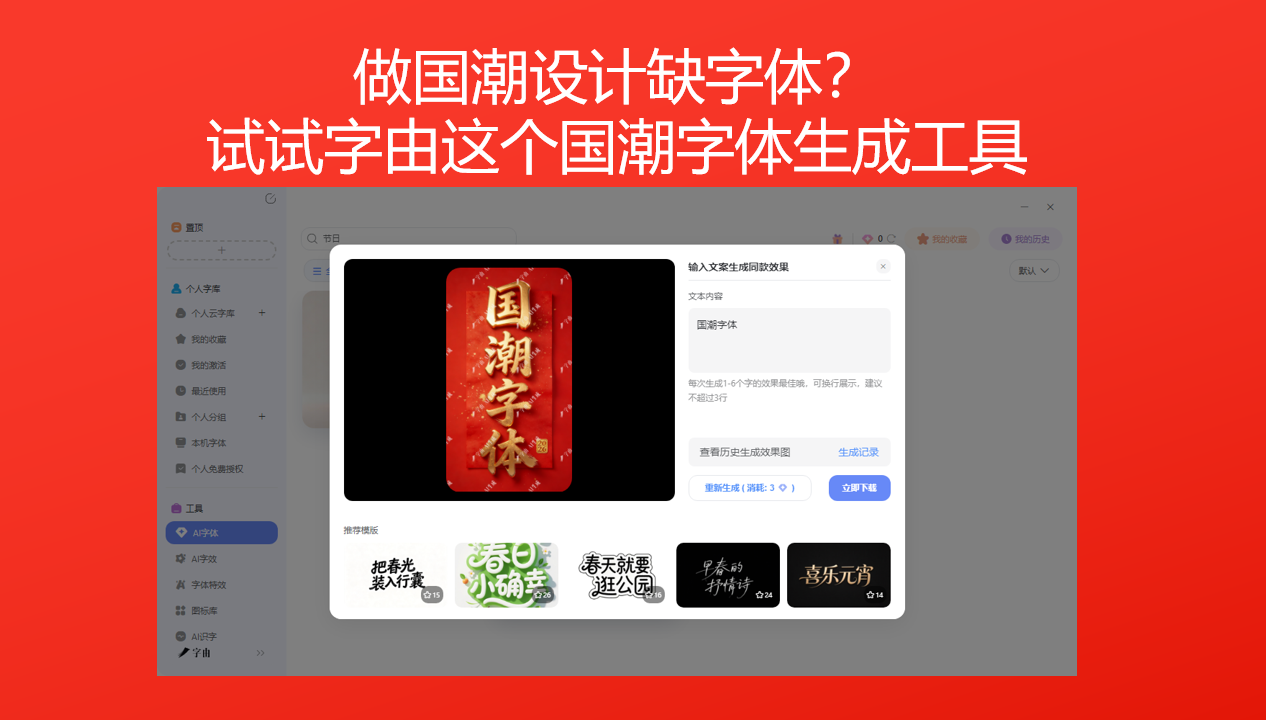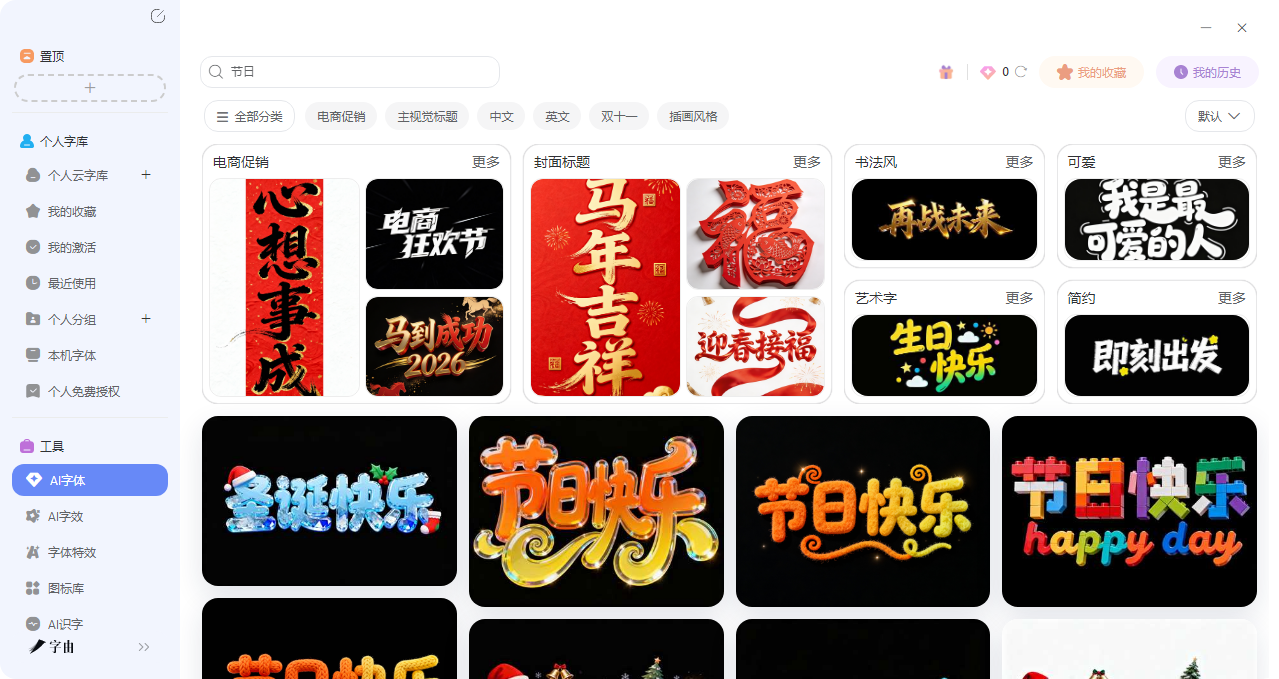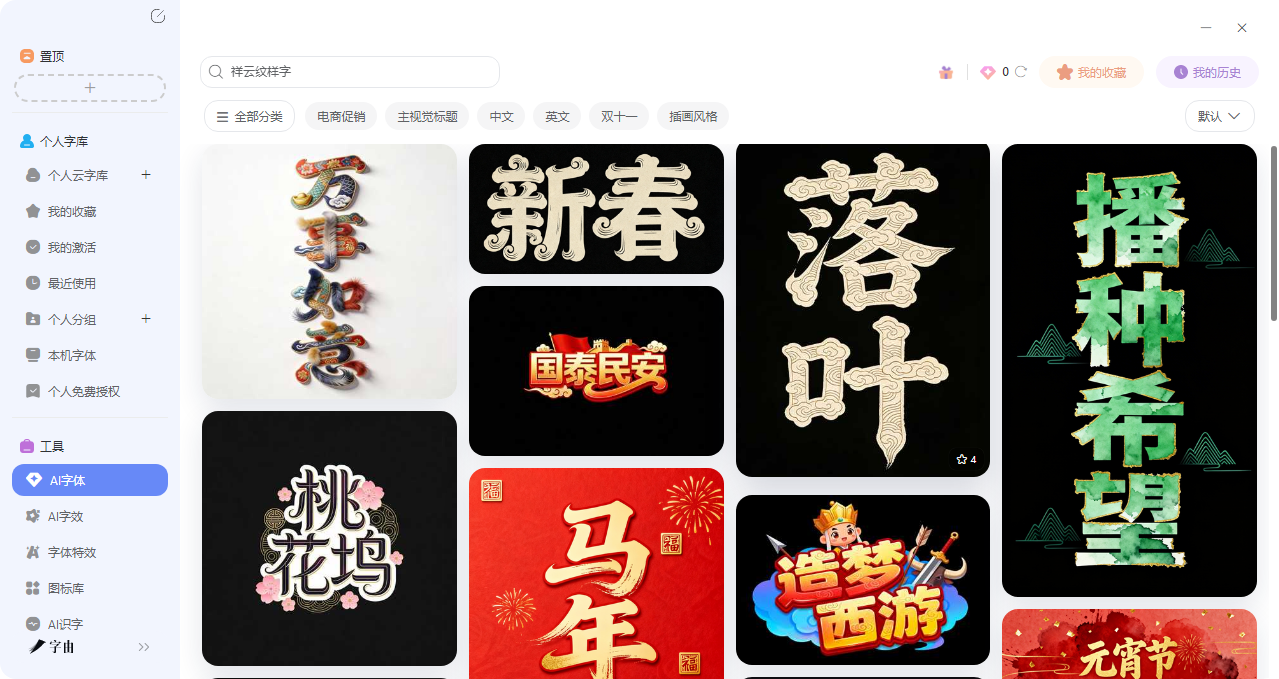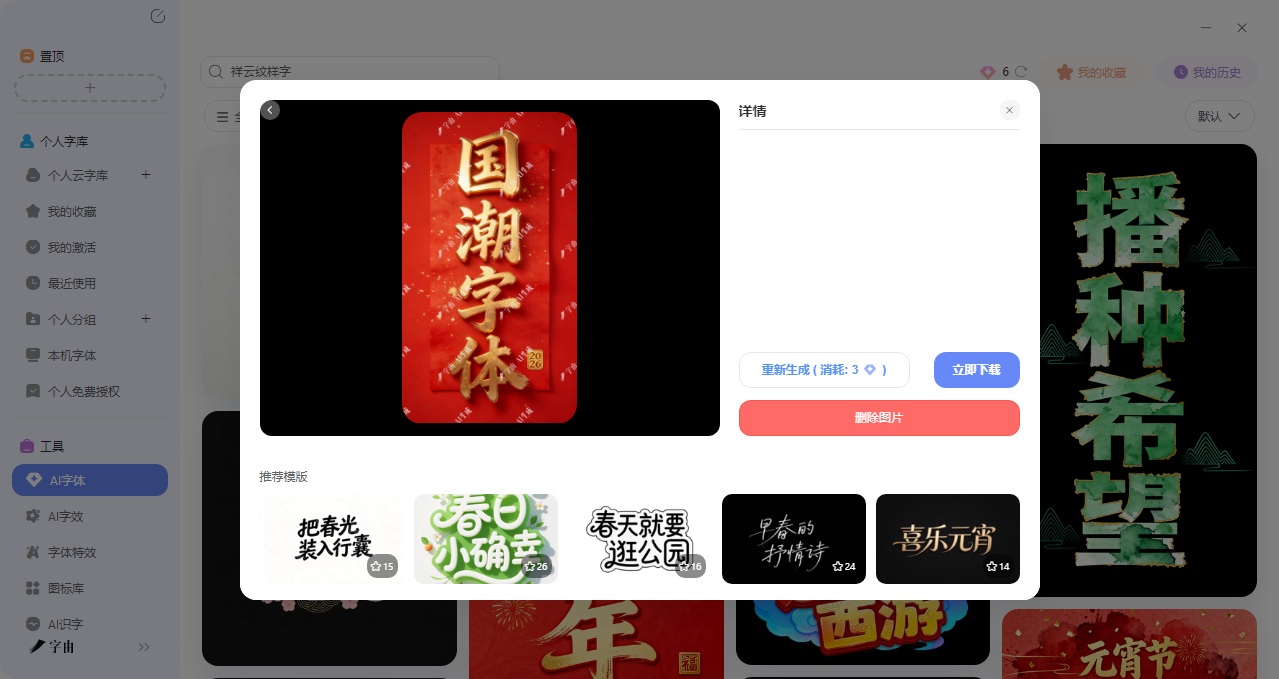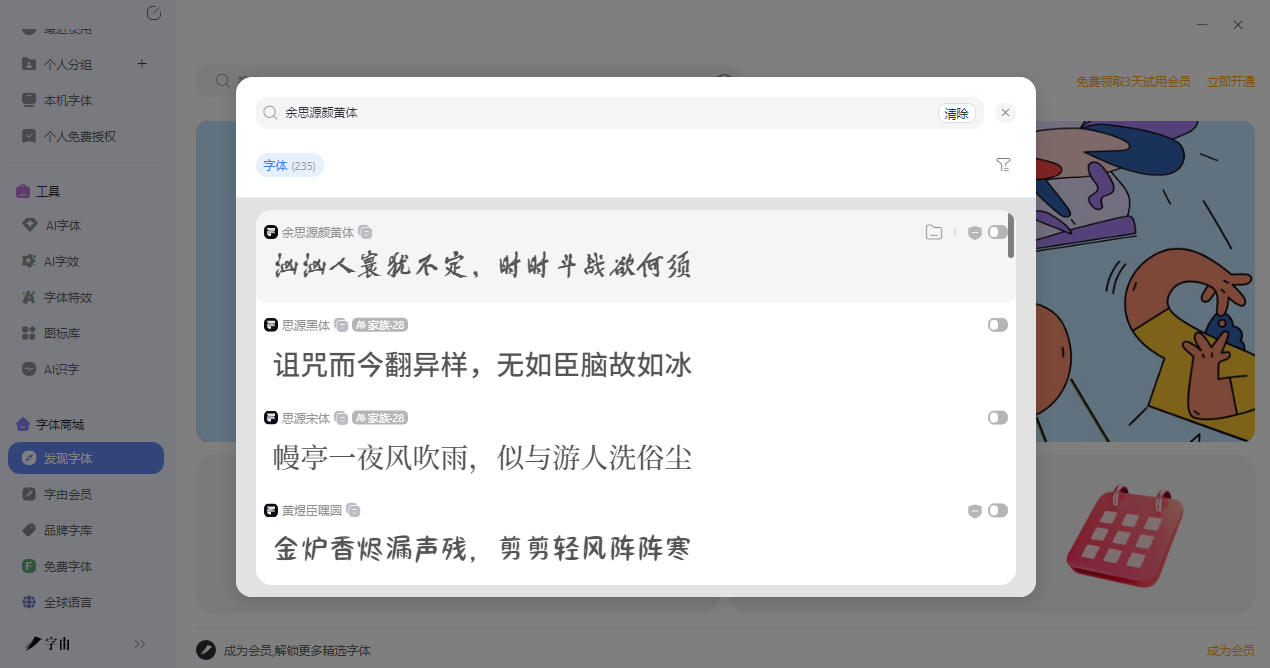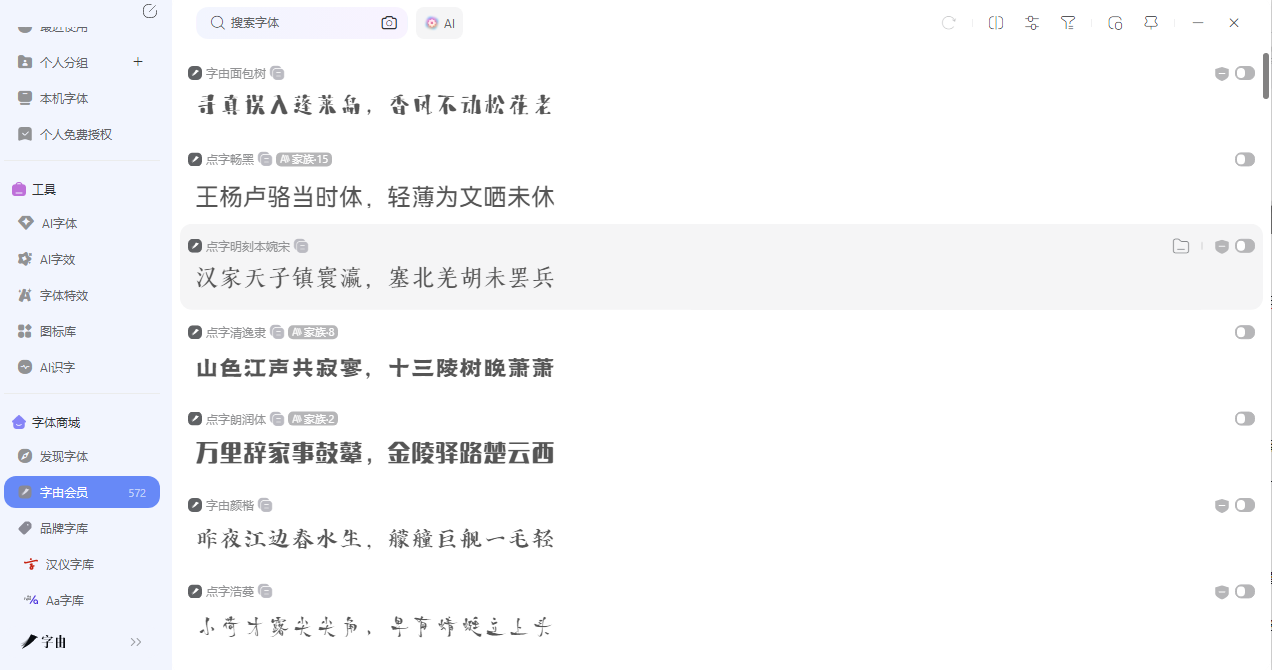
做国潮设计缺字体?试试字由这个国潮字体生成工具
近几年国潮的热度可谓是居高不低,相信做设计的都应该深有体会。从品牌包装到文创周边,再从电商海报到一些短视频封面,几乎每一处你都能看到国潮的身影。但是那些精美的国潮字体真的是需要一板一眼地精心设计出来吗?也许一开始是要的,但是现在我可以告诉你,用一个工具就可以在10 秒内生成出来一款非常精美的国潮字体,并且还有很多国潮书法体字体供你免费下载使用。那今天这篇我就来专门讲一下,怎么用字由搞定国潮设计里的字体问题。
1、如何用字由生成国潮字体?
字由的AI 字体功能是专门用来生成艺术字效果的,其中就包括了各种国潮字体。并且你不用自己慢慢调图层样式,也不用到处找教程,选个模板、输入文案、点一下生成,几十秒就能拿到可用的国潮字体图。
接下来我会教你详细的步骤来制作AI 国潮字体。
• 第一步:浏览模板。进入AI字体页面后,你会看到各种风格的字体模板,按场景分好了类:电商促销、LOGO设计、Banner设计、国潮风、书法风等。想找国潮字体,可以直接点“国潮风”分类,或者搜索关键词“国潮”“书法”“中国风”。
• 第二步:选择模板。模板库里有很多国潮风格的选项,鎏金书法字效果,水墨晕染字效果,印章式文字效果,祥云纹样字效果,碑刻拓印效果等等,每个模板都有预览图,点进去可以看大图。挑一个和你设计主题搭的。
• 第三步:输入文案。选好模板后,点击“做同款”,进入编辑页面。在输入框里填你的品牌名、标题或想要生成的文案。需要注意的一点是:最好和模板的字数保持一致,这样生成的效果最自然。比如模板是四个字,你就填四个字;模板是两个字,你就填两个字。
• 第四步:点击生成。确认文案后,点“立即生成”,等25-30秒左右,系统就会输出设计好的国潮字体图。生成后可以预览效果,不满意可以微调文案再生成,每天有免费算力点,不够用的话1元买10点,试错成本极低。
第五步:下载使用。生成满意后,点击下载。可以把背景调成透明,直接保存PNG格式,然后拖进PS或AI里继续排版。
到这里为止,一份国潮字体就这样免费下载好了!是不是十分简单?并且字由内置的多款AI 字体绝对够用,再加上每天免费送的 6 算力点也十分划算,就算你不用字体,每天上去签个到,日积月累下来相当于不花钱。
2、AI字体生成的小技巧
上面说完了AI 字体生成的方法, 那么下面我还会给大家介绍一下生成的小技巧。
• 多试几个模板:同样的文案,换不同模板效果差很多。花几分钟多试几个,找到最对的那款。
• 注意字数匹配:模板的设计是基于特定字数的,字数差太多容易变形,尽量保持一致。
• 透明背景最实用:下载时选透明背景PNG,后续排版更方便。
• 结合其他工具用:生成的字体图可以再进PS加纹理、调色,做出更丰富的效果。
3、字体推荐
除了AI生成,字由本身就有大量现成的国风字体。下面按风格分类推荐一些:
程荣光刻楷:经典楷书风格,端庄规整,笔画清晰。适合正式一点的传统文化内容,比如书法展览、古籍类设计、中式婚礼请柬。
余思源颜黄体:模仿颜真卿和黄庭坚风格的字体,大气稳重,笔画有力。适合国潮品牌、中式美学类封面、电影海报标题。
点字清逸隶:隶书风格,但比传统隶书更清秀一些,没有那么厚重。适合做茶品牌、文房四宝、中式餐饮的包装设计。
汉仪黄科壮隶:汉仪出品的隶书字体,笔画饱满,结构稳重。适合需要历史感的设计,比如博物馆文创、古风游戏界面。
点字浩蔓:飘逸灵动的手写体,比芳华体更洒脱一点。适合国潮文创、旅行日记、文艺类封面。
4、怎么把这些字体用到设计里?
找到喜欢的字体只是第一步,怎么用到图上才是关键。字由最方便的地方就是“一键应用”。具体操作如下:
1. 打开PS(或AI、Figma等设计软件),新建画布
2. 用文字工具输入你的标题文案
3. 打开字由客户端,找到刚才看中的字体
4. 在PS里选中文字图层,回到字由点一下字体——文字瞬间切换
整个过程不需要下载、安装、重启软件,试一款字体只要1秒钟。你可以一口气试几十款国风字体,找到最适合的那一个。
总之,国潮字体设计找字由就对了,字由的AI字体生成功能,让你能快速获得专属的国潮艺术字;如果你又想要一些国风字体来辅助设计,首选也肯定是字由,因为它庞大的字体库里面总会有你需要的那一款,并且还能够支持你去匹配不同的设计场景。如果你还在为字体这件事情发愁,不如直接打开字由,里面会有你想要的答案。